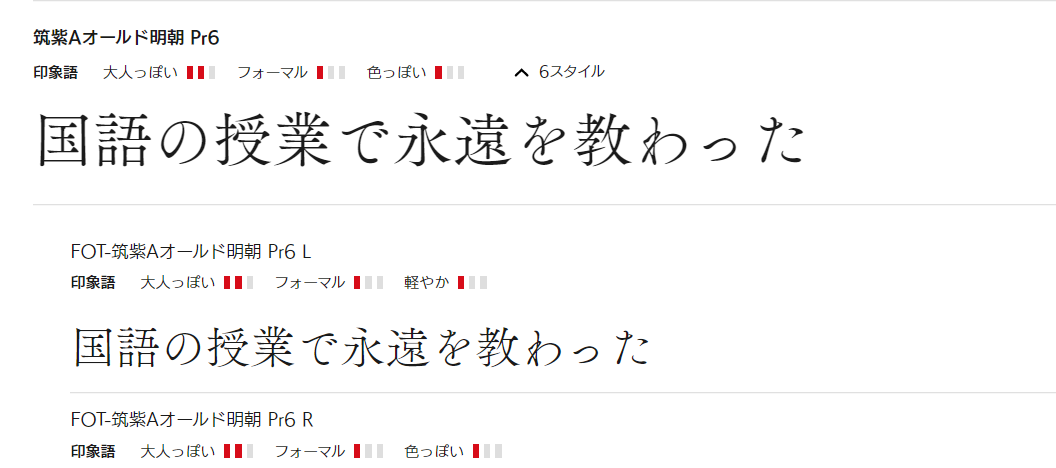
「LETS」で印象語からフォントを検索できる機能「印象語検索AI(β版)」が提供開始
フォントワークスは、2022年3月30日に年間定額制フォントサービス「LETS」に、「印象語」からフォントを検索できる新機能「印象語検索AI(β版)」を追加したことを発表した。
「印象語検索AI(β版)」は、九州大学との共同研究に基づき開発した、文字のデザインに対するイメージを表現する「印象語」からフォントを検索できる新しい機能。
フォント選定の時間短縮や、表現したいデザインの「イメージ」「印象」に合わせたフォント選びに使用できる。
「印象語」について
印象語とは、人が文字のデザインに対して感じる抽象的なイメージを単語に表現したもの。
β版では、研究に基づき選定された5つの分類「感情、形状の印象、性格、擬人、精神状態」からなる36単語が各日本語フォントに登録されている(β版の印象語とフォントの紐付けはフォントワークスの書体デザイナーにより設定)。
今後は統計データ収集により印象語とフォントの紐付け精度の向上、必要とされる印象語の拡充、検索機能の向上を図る。
2022年4月現在登録されている印象語(36語)
感情:かわいい、凄い、気持ちいい、面白い、心地よい、心強い、迷い、怖い、切ない、憎い、きつい、つらい
形状の印象:ハード、ソフト、フォーマル、カジュアル、重圧感、軽やか、こってり、あっさり、可憐、力強い
性格:幼い、大人っぽい、素朴、親しみ、真面目、ピュア、無邪気
擬人:スマート、色っぽい、かっこいい、シック、フェミニン
精神状態:癒し、元気
「印象語検索AI」開発プロジェクト
フォントの更なる可能性を求めて、フォントから受ける印象に関する性能を学術的観点で求めるべく、九州大学と共同研究を実施。
研究結果をもとに発足した「印象語検索AI」開発プロジェクトは、『フォント自身が持つ印象誘起性』を明確化することで、デザイナーのフォント選択を支援するサービス提供を目的としたプロジェクトとなる。
現在は印象語での検索のみだが、文章や画像、人物名などでも検索できるよう、今後も開発を進めていくそうだ。
・フォント選定の時間を短縮したい。
・デザイン提案時に後押しとなるエビデンスを提示したい。
・デザイナー以外の方や学生でデザインの知識がなくても適切なフォント選定を行いたい。
絞り込みたい印象語を複数選択して検索すると、登録されている印象語と一致する度合いが強い順に検索結果に並ぶ。
検索結果に対し印象語分類ごとのソート機能を使用することで、各分類に属する印象語との一致度合いが強い順に並び替えることができる。
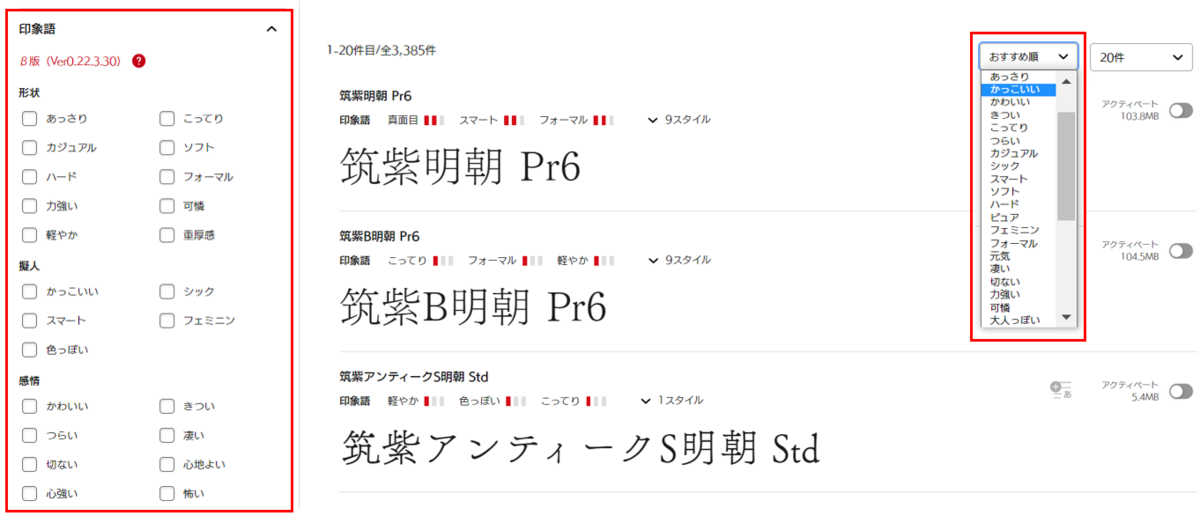
1.1つのフォントにつき印象語が3段階評価で登録されている。
2.同じファミリでもウェイトごとに異なる印象語数値を持っている。
3.一覧画面では、各フォントに登録されている印象語のうち、数値の高い上位3語が表示される。